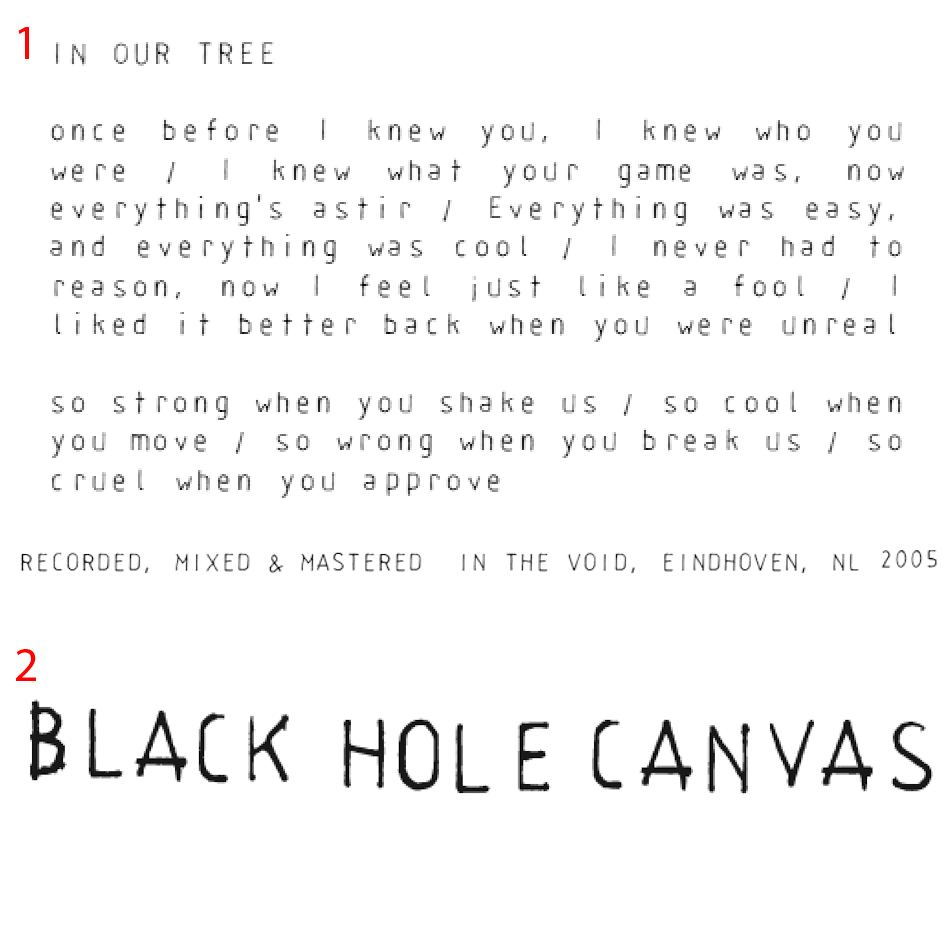
Wer kennt die Originalnamen?
ich bin mittlerweile darauf gekommen, das der Grafiker seinerzeit die Fonts umbenannt hat (Warum auch immer). Neben dem von mir gestern gesuchten Font (neuer Name „Hole“) gibt es auch noch eine etwas fettere, anders gestaltete Schrift (2). Alles aus Mitte der 2000er Jahre, irgendwie nicht unbekannt, allein es fehlt der Name. Anbei ein Bild mit Beispielen.